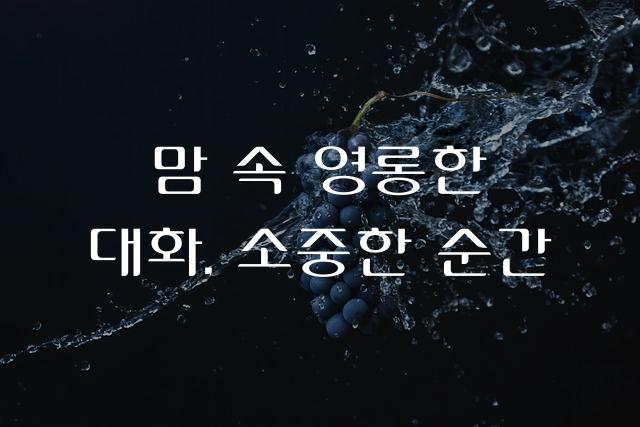
대화나눔 본문체는 대화제약에서 제작한 한국어 폰트로, 따뜻하고 친근한 감성을 전달하는 데 최적화되어 있습니다. 이 폰트는 부드러운 곡선과 균형 잡힌 구조로 독자의 눈을 편안하게 해줍니다.
대화나눔 본문체은(는)
계열의 생김새를 가지고 있으며
교육 자료, 보고서/문서, 출판물 제목 등에서 자주 활용되며, 효과적인 메시지 전달에 적합합니다.
이 폰트는 교육, 출판/미디어, 문화/예술 분야에 잘 어울리며,
친근한, 편안한, 단순한 느낌을 담고 있는 것이 특징입니다.